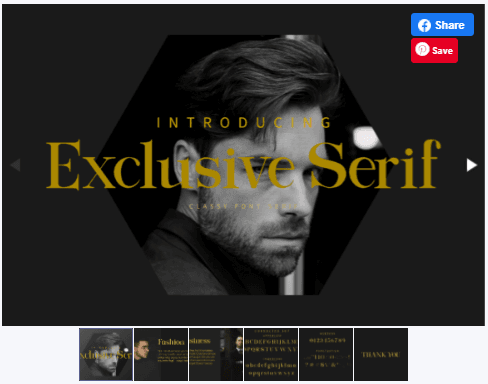
Exclusive Serif Font
Exclusive Serif - элегантный и стильный шрифт с засечками. Он прекрасно смотрится на различных дизайнах, требующих индивидуального стиля, таких как свадебные приглашения, открытки с благодарностью, свадьбы, поздравительные открытки, логотипы и так далее.